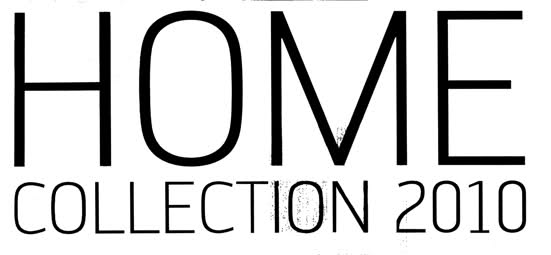
Groteskschrift gesucht
vielen Dank - kommt schon sehr nahe, ähnlich wie die Zemestro oder Stainless - aber das besondere dieser Schrift treffen sie nicht.
ich habe auch einige ähnliche Schriften, aber keine echte Passung. :?
Daher würde ich einen anderen Ansatz probieren. Woher kommt die Abbildung (Scan)? Wer ist der Urheber? Gibt es von denen WWW-Seiten oder Dokumente im WWW? Kannst Du auf diesen Seiten PDF-Dateien finden? Notfalls kannst Du diese mit Google, Ask oder Co suchen. Dann schau mal nach welche Schriften eingebettet sind.
Gleich die zweite: Engel von Sofie Beier sieht gut aus:
Ist das vielleicht sogar die frei verfügbare Engel Light?